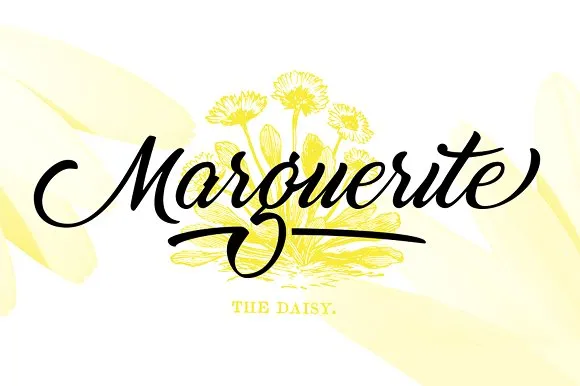
A fonte ‘Marguerite Font’ é uma elegante e suave tipografia script que captura a essência do estilo da grafia francesa conhecida como Daisy. Suas curvas são fluidas e sutis, criando um sentimento de frescura e naturalidade em cada caractere. Esta font é perfeita para textos delicados ou design gráfico orientado para o artesanato. A versão comercial completa inclui uma seleção de gírias alternativas e ligações, oferecendo a Hamilton designers e criadores um recurso refinado com flexibilidade incrível. Uma ótima font para adicionar autenticidade aos seus trabalhos de arte ou projetos que valorizam o cuidado detalhado.